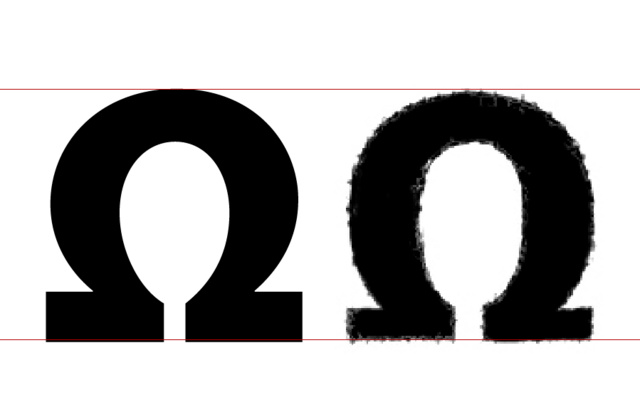
kennt jemand diese Schrift?
kennt jemand diese typo hier (die rechte! / links zum vergleich die Myriad)?
näher als bis zur myriad pro bin ich nicht gekommen!
Hast Du noch weitere Buchstaben der gesuchten Schrift, die Du uns zeigen könntest? Anhand dieses einen Zeichens dürfte es vermutlich recht schwierig werden, die Schrift zu identifizieren.
ja hier. leider keine schöne quali:
andere Zeichen aus der Schrift hast Du also keine?
Und: Hast Du schon mal gezielt nach Egyptienne-, bzw. Slabserif-Schriften gesucht?
Die Serifen Deines Zeichens deuten auf eine solche Schrift hin.
hilft mir leider nicht, da verwendetes zeichen keine frutiger ist, jedenfalls keine mir bekannte ...